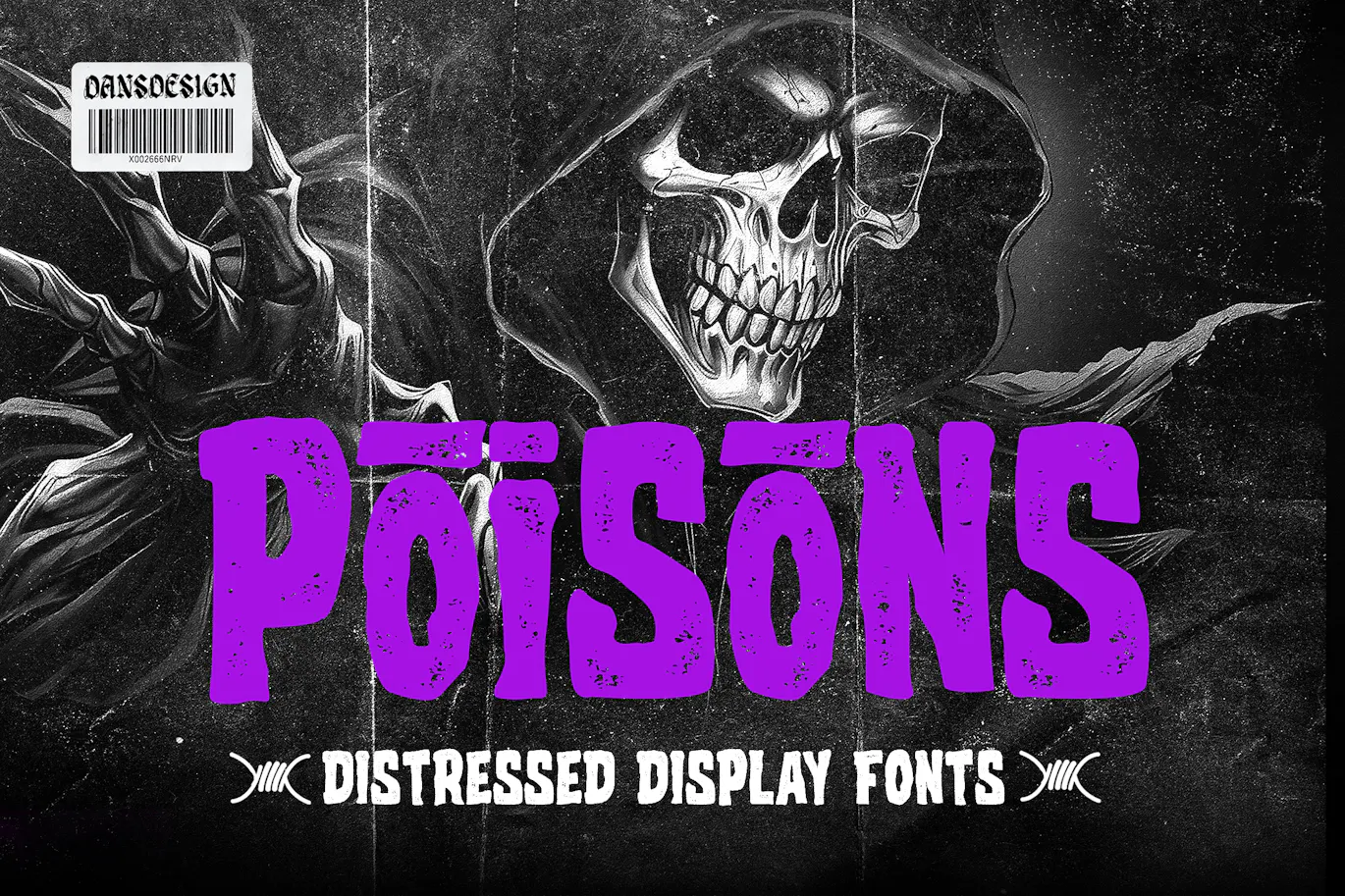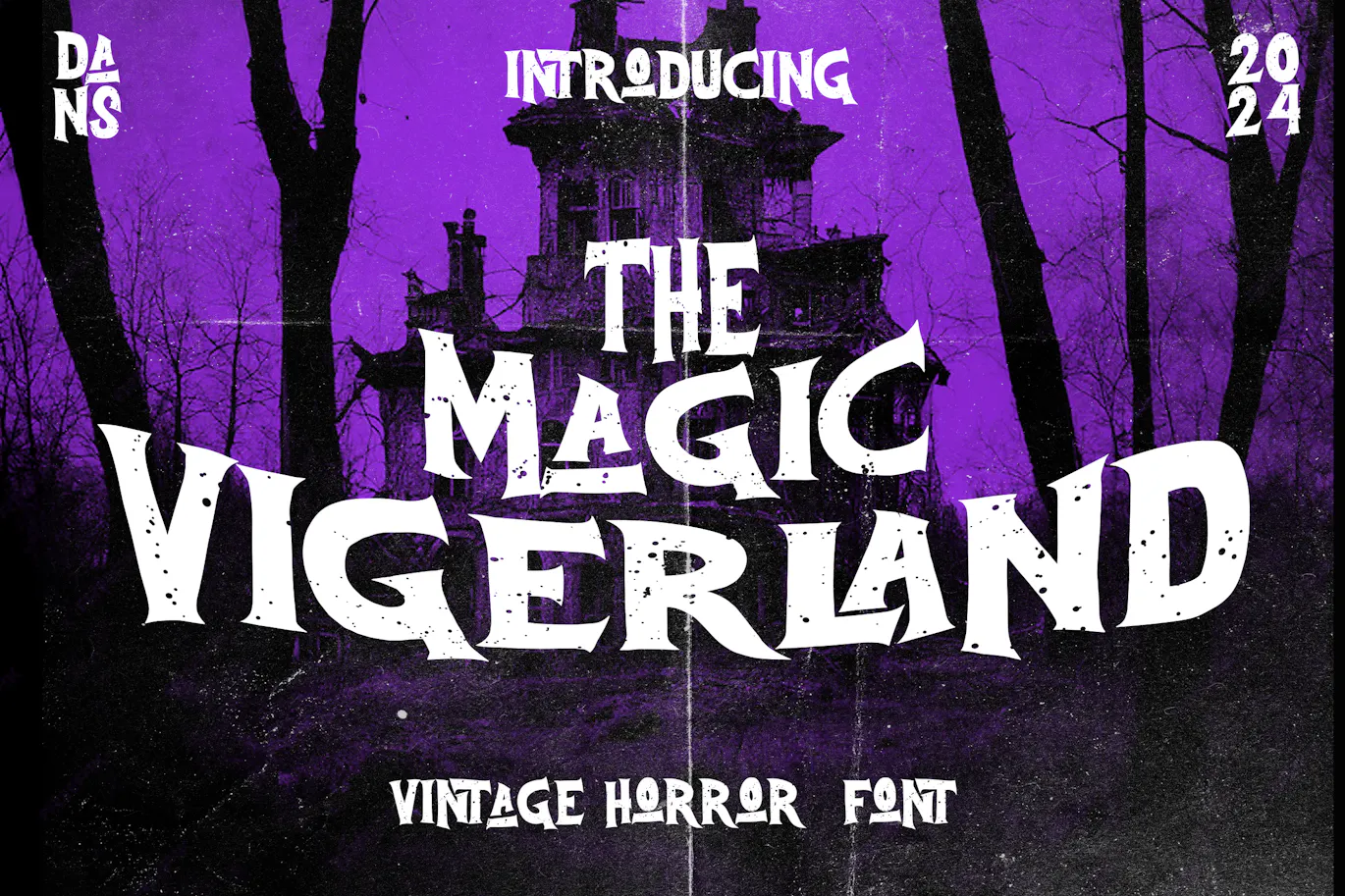
复古恐怖卡通漫画的英文装饰标题字体 – Poisons
Poisons是一款复古恐怖卡通漫画的英文装饰标题字体,现代仿旧字体它将成为精致的复古城市设计、商业品牌、标志、服装设计等的绝佳选择。字体格式有OTF/TTF。- 44
恐怖感的英文复古涂鸦画笔字体 – Dameter Horror
Dameter Horror是一款恐怖感的英文复古涂鸦画笔字体,独特、高度详细且别致的 Blackletter 字体。它是精致的复古城市设计、纹身商业品牌、徽标、复古设计、电影、海报、服装、插图等的绝佳选择。字体格式有otf、ttf。- 406
复古风恐怖金属风格的英文纹理涂鸦字体 – The Magic Vigerland
The Magic Vigerland是一款独特、恐怖金属风格的Y2k涂鸦字体。它是精美音乐、海报、复古城市设计、商业品牌、标志、复古设计等的绝佳选择。- 53